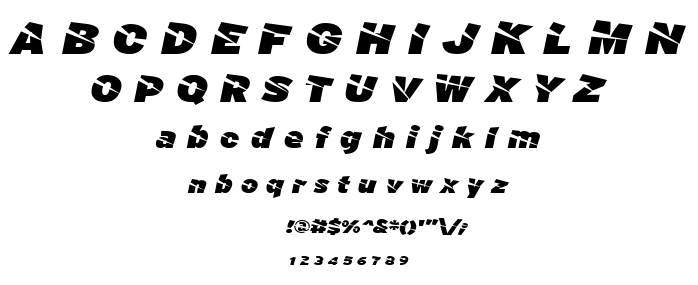
La tipografía Acuchillada es un experimento expresionista del dolor del autor por la muerte prematura de un gran amigo. Intentando refugiarme en el diseño de letras y en un impulso ciego, la acción de acuchillar la fuente surge sin reflexión, sin ánimo pero con rabia, como respuesta a la sin respuesta de la desaparición temprana de un afín, Carlos de pejino.com (.+. 02/09/14).